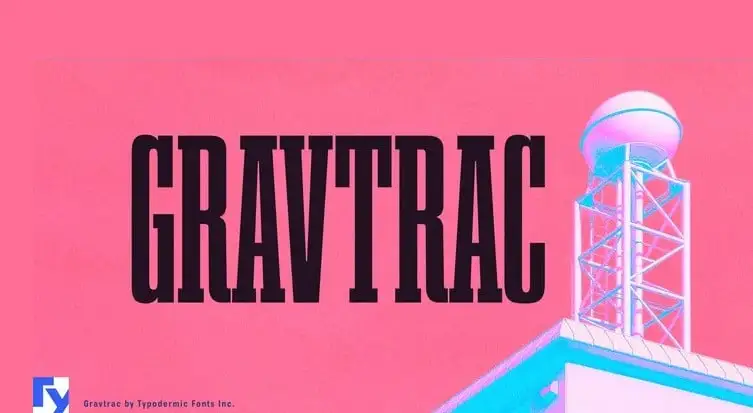
A Gravtrac Slab Serif Font é uma nova adição à gama de tipos de texto para designers profissionais, trazendo com ela uma modernidade que combina bem com projetos de marca e identidade visual. Inspirada nos clássicos da década de 1950, esta fonte proporciona um aperto eficaz, enquanto acomoda muito material na horizontal. O design da Gravtrac é focado em linhas retas, ritmos sólidos e curvas precisas. Essa fonte destaca-se com uma série de pesos de negrito desde Ultra-Light até Heavy, incluindo um estilo Condensed compacto e confortável para leitura, perfeito para uso em formatos mais estreitos. Mas o que realmente torna a Gravtrac inovadora é sua capacidade de se ajustar. Há uma opção chamada Gravtrac Crammed, extremamente estreita até onde os outros tipos de fonte podem ir, combinando perfeitamente com um espaçamento horizontal mais largo para criar um visual marcante e elegante. Além disso, cada estilo inclui pesos em obliques que variam entre 7º a 10º, oferecendo uma gama total de cerca de 58 estilos. A Gravtrac também abrange caracteres numerários em tipos romanos padrão (numerais de cotação), além de símbolos monetários e numerais arábicos do tipo antigo ou “old-style” (minusculo). Esta fonte é compatível com quase todos os idiomas baseados na língua latina, incluindo grego e cirílico. Seja para estilos mais legíveis ou um pouco mais elaborados, a Gravtrac Slab Serif Font tem tudo o que um designer pode precisar em uma única fonte.